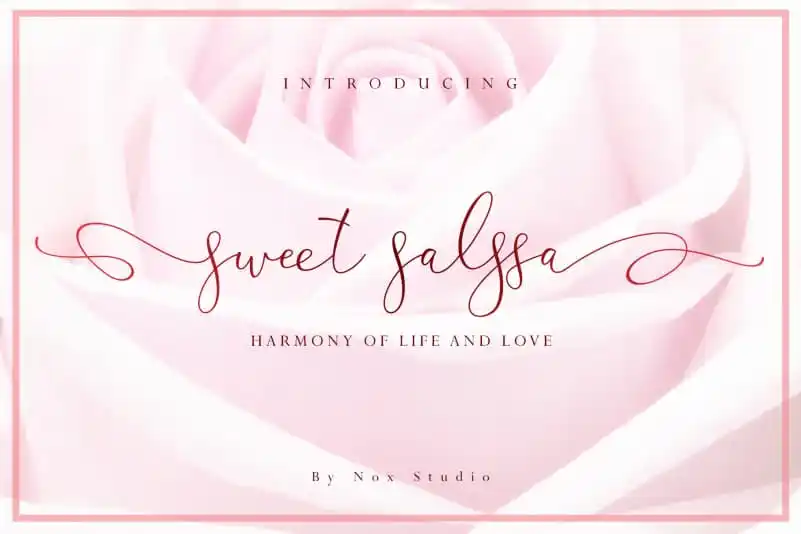
Sweet Salssa Calligraphy Font – Download Grátis
Sweet Salssa Calligraphy Font é uma elegante tipografia de calligrafia criada pela Nox Studio, com uma base-alinha desequilibrada que adere perfeitamente ao seu estilo. Ideal para aqueles que buscam um toque de amor e modernidade em seus designs ou marcas de imagem, este fonte se destaca não apenas por sua beleza singular, mas também pela sua versatilidade. Com Sweet Salssa Calligraphy Font, você pode incorporar o ar suave da calligrafia na criação de variados materiais como cartões de aniversário e convites para casamentos, assinaturas pessoais ou empresas, logotipos, camisas personalizadas, etiquetas de embalagem, placas de avisos e até mesmo em sua próxima publicação impressa. Este fonte é um verdadeiro tesouro para todos os criadores que procuram dar uma nova dimensão a suas criações com estilo único.